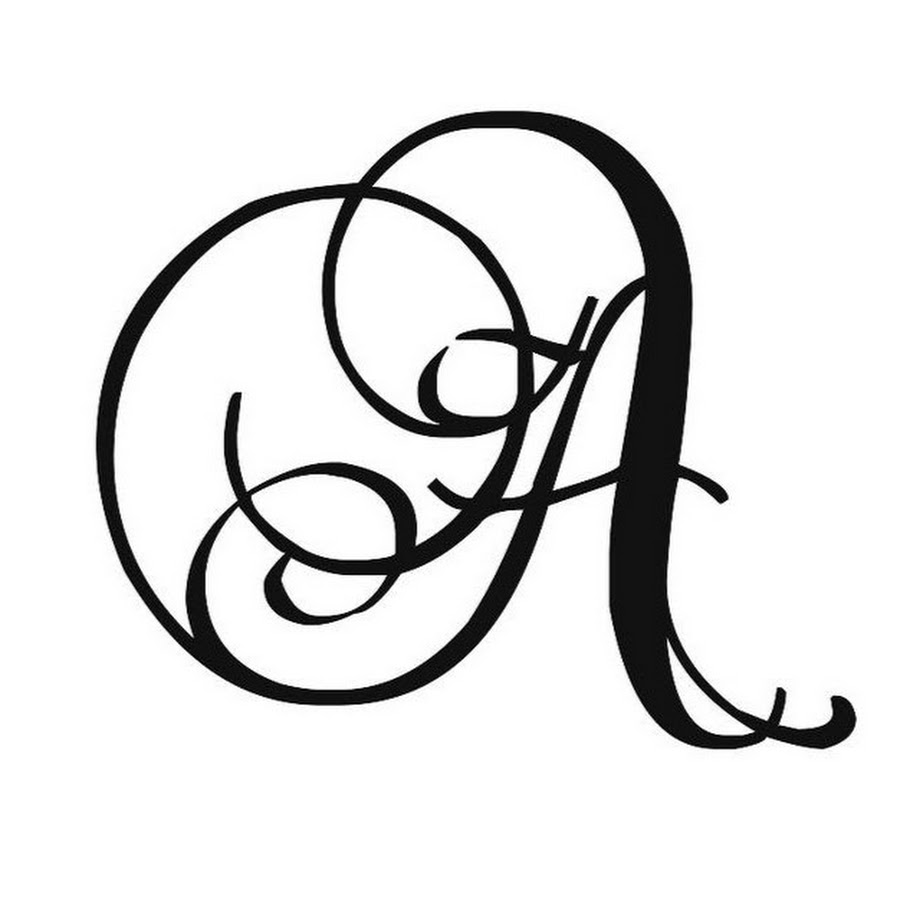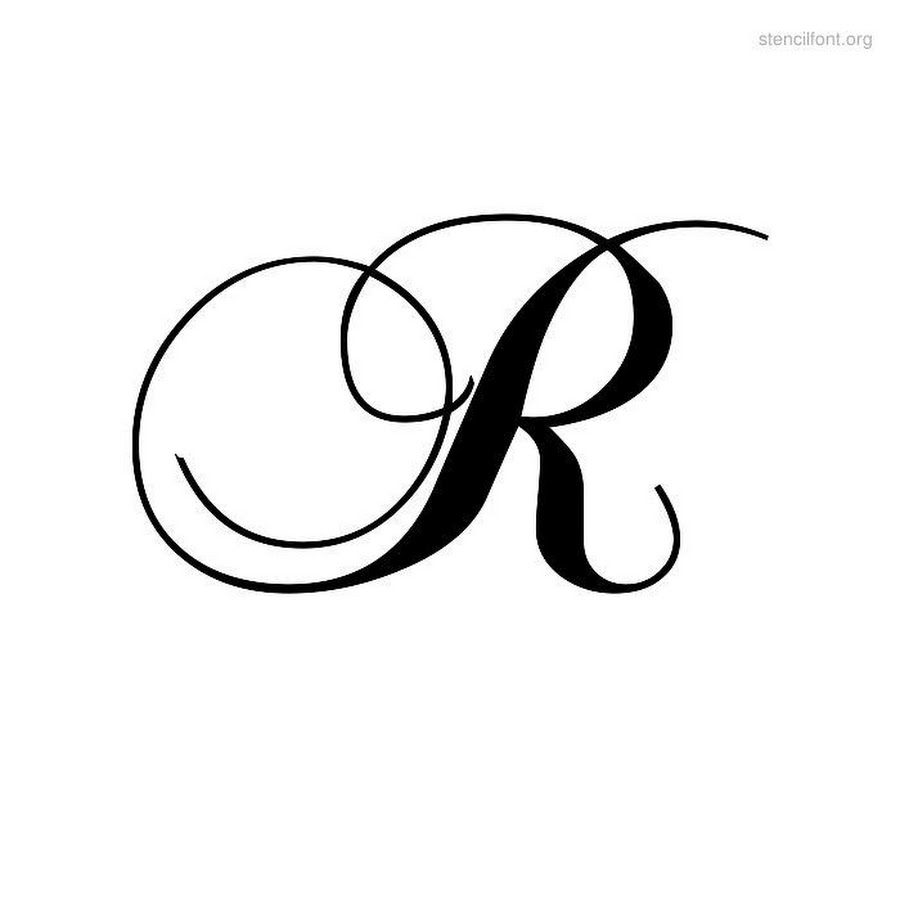
Тату буквы эскизы: интересные идеи, шрифты, стили написания
Тату инициалы: значение, фото татуировки, эскизы
Татуировка инициалы, фото которой представлены в статье, может смотреться очень оригинально и необычно. Главное — это правильно выбрать эскиз и хорошенько продумать, где будет располагаться будущий рисунок!
Значения
Татуировка с инициалами может иметь несколько значений. Некоторые люди делают такие тату с первыми буквами собственного имени. Такое изображение может говорить о том, что человек ценит и уважает себя. Не стоит думать, что подобные тату — свидетельство самовлюбленности. Скорее, это выражение нормального эгоизма и ощущения ценности собственной личности.
Нередко люди украшают тела татуировками инициалы, эскизы которых можно увидеть в статье, нанося на кожу первые буквы имен членов своей семьи. Эти тату говорят о том, что носитель татуировки ценит своих близких и готов ради них на многое. Иногда такие татуировки делают молодые мамы, увековечивая на теле инициалы своего малыша.
Инициалы в виде татуировки тонким шрифтом
Наконец, часто можно увидеть тату с инициалами любимого исполнителя. Подобные изображение наносят на тело молодые люди, которые могут фанатично обожать группу или певца и воспринимать харизматичную знаменитость как ролевую модель.
Инициалы в медальоне на предплечье
Совет! Не стоит наносить на тело инициалы возлюбленного или возлюбленной. Такой поступок может оказаться неосмотрительным: в случае расставания придется потратить много времени и финансов на то, чтобы вывести или перекрыть тату.
Инициалы с пером в виде тату
Стили исполнения
Татуировки инициалы, значение которых описано выше, выполняются в различных стилях. Стоит изучить их прежде, чем отправляться в салон, ведь даже буквы могут стать настоящим произведением искусства, если выполнены талантливым мастером по индивидуальному эскизу:
- олд-скул и нью-скул.
Яркие и необычные татуировки в этих стилях дополняются различными элементами, например, лентами, черепами, цветами, ветками и т. д. Благодаря этому рисунок будет смотреться стильно и вы сможете внести в него интересную идею; - треш-полька. Тату в стиле треш-полька обычно бывают достаточно крупными, поэтому инициалы в них служат дополнительными элементами. Выполняются тату в этом стиле преимущественно в черном и красном оттенках;
- гравюра. Объемные графичные буквы могут стать отличной идеей для оригинальной, лаконичной тату. Чтобы рисунок был более объемным и ярким, можно дополнить его цветными разводами;
- дот-ворк. Тату в стиле дот-ворк представляют собой изображения из точек разного диаметра. Инициалы в этом стиле можно обыграть очень интересно, например, сделав «тающие» или «плохо пропечатанные» буквы.
Тату инициалы тонким шрифтом
Совет! Не стоит просить мастера, чтобы он сделал инициалы шрифтом, который имеется в стандартных офисных программах! Это редко смотрится оригинально и интересно. Лучше, чтобы тату была создана по индивидуальному эскизу, только так вы сможете быть уверены в ее неповторимости и художественной ценности.
Татуировка инициалы ВА
Идеи для тату с инициалами
Интересно будет смотреться тату с инициалами, в качестве эскиза которой использован детский рисунок. Иногда такие татуировки делают родители, попросившие детей написать первый в жизни буквы. Подобные тату всегда выглядят оригинально и очень трогательно.
Красиво выглядят инициалы в виде вензелей или стилизации под буквы в рукописных средневековых трактатах.
Популярностью пользуются инициалы, которые словно «вырезаны» на коже или на коре дерева.
Решили увековечить на теле свои инициалы или инициалы близких людей? Осталось только обдумать свою идею, и, если решение окончательно, отправляться на поиски мастера, который достойно выполнит поставленную задачу!